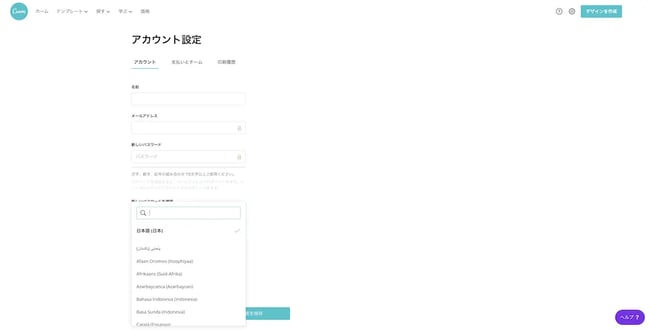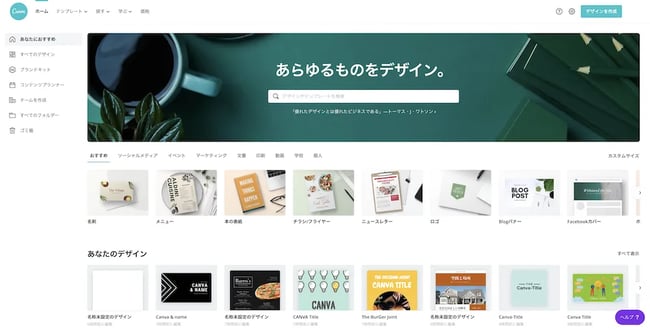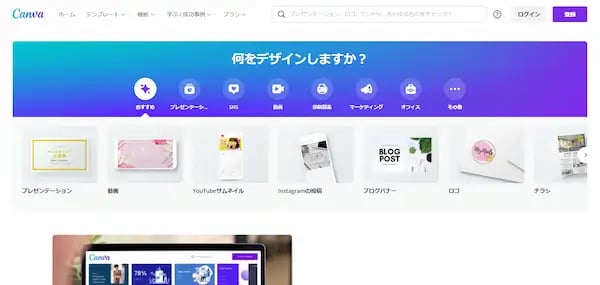
【Canva】無料で使える日本語フォントまとめ&選び方のコツを解説
手軽に高品質なデザインが作れると話題のCanvaは、実は日本語フォントが充実しています。ただ、使える日本語フォントが多すぎて、どれを選べば良いか迷う方も多いのではないでしょうか。
読みにくくなってしまったりデザイン全体と噛み合わなかったりと、ユーザー体験を損ねてしまう可能性があります。本記事では、Canvaの無料日本語フォントをまとめてご紹介した上で、フォント選びの基準や、日本語フォントを使えない場合の対処法も解説します。
Canvaとは
無料で使える豊富なテンプレートを活用することで、誰でも魅力的なデザインを作成できるデザインツールが「Canva」です。すべての人がデザインを自由に楽しめるよう支援することを目的に作られたツールで、1人ひとりがデザインの力で輝くことをミッションに開発されています。出典:PR TIMES
2021年時点で、無料で使えるテンプレートは25万点以上にも上り、ロゴやSNS投稿画像、YouTubeサムネイル、プレゼンテーション、チラシなど、さまざまなデザインが作成できます。PC版とスマホ版があり、PC版ではブラウザで利用できる点も特徴です。
Canvaには無料プランの他に有料プランとしてProとEnterpriseがあり、使用できるテンプレート数やチーム向け機能などに差があります。とはいえ、無料プランでも十分な機能性があり、個人や小規模チームを中心に広く利用されています。
Canvaの無料日本語フォント
Canvaでは日本ユーザーの声に応え、2021年8月に大量の日本語フォントを追加し、合計で309種類の日本語フォントを利用できるようになっています。一部は有料プランでのみ利用可能ですが、250を超えるほとんどの日本語フォントは無料プランで利用可能です。
では早速、Canvaで使える無料の日本語フォントの一部を紹介します。気になったものがあれば、デザイン作成時に試してみましょう。
ゴシック体
まずはゴシック体フォント9つです。
UD丸ゴ_ラージ
UD丸ゴ_ラージは、人気の丸ゴシック体の「スーラ」をベースに、モダン性を向上させたフォントです。スーラと比較して字面が大きくし、視認性と判別性が向上しています。
JKゴシック
JKゴシックJKゴシックは、その名の通り女子高生が書きそうな文字を意識した、全体丸みを帯びたフォントです。
さわらびゴシック
さわらびゴシックは、小さめの字であっても可読性が高いことが特徴的です。
せのびゴシックBold
せのびゴシックBoldせのびゴシックは、従来の「M+」フォントを全体的に縦に引き延ばしたような形で作られたフォントです。デザイン性を保ちながらも無機質な印象を与えます。
せのびゴシックRegular
やさしさゴシック
やさしさゴシックは、一般的なゴシック体と比べて、その名の通り「やさしさ」をコンセプトにおいたフォントです。漢字の対応も充実しています。
ロゴたいぷゴシック
ロゴたいぷゴシックは、その名の通りロゴや見出しに適したフォントで、角ばった印象と優しい印象が共存しています。
刻ゴシック
刻ゴシック刻ゴシックは、ゴシック体の形を保ちながらも、平仮名やカタカナは全体的に直線的な形を取り入れたフォントです。
ぼくたちのゴシック2
ぼくたちのゴシック2は、ぼくたちのゴシックからリニューアルしてできたもので、はねと丸みが印象的です。
明朝体
次は明朝体フォント7つです。
XANO明朝フォント
XANO明朝フォントは、手書き風に近いフォントで、各文字の書き出しなどに筆で書いたような墨溜まりが反映されています。
こころ明朝体
こころ明朝体こころ明朝体は、全体的に細めながらも、書き始めと書き終わりが丸くなっている点が印象的なフォントです。
はれのそら明朝
はれのそら明朝はれのそら明朝は、適度に一画が細く、こころ明朝体同様に墨溜まりが見られるような温かい印象を与えるフォントです。
はんなり明朝
はんなり明朝はんなり明朝は、平仮名とカタカナに特化したフォントです。それ以外の、漢字やアルフベットについては、IPA明朝体で表記される仕様になっています。
ほのか明朝
ほのか明朝ほのか明朝は、オーソドックスな明朝体をベースに、柔らかい曲線を取り入れたフォントです。
刻明朝
刻明朝刻明朝は、通常の明朝体がベースとなり、平仮名とカタカナのみを他よりも小さく設定して作られたフォントです。やや固めの印象を与えます。
梅明朝
梅明朝梅明朝は、梅フォントとも呼ばれ、源ノ角ゴシックと対の関係にあるようなフォントです。
行書体・筆文字系
行書体および筆文字系のフォントは5つあります。
おつとめフォント
ダーツフォント
みかちゃん
花鳥風月
衡山毛筆
手書き風
手書き風フォントは7つあります。
851チカラヅヨク
しねきゃぷしょん
はなぞめ
ふい字
たぬき油性マジック
桜鯰フォント
無心
その他
最後に、様々な独自フォントをご紹介します。全部で38個あります。
M+ 1m Bold
M+ 1m Regular
M+ 1m Thin
M+ Bold
M+ Heavy
M+ Rounded Black
M+ Thin
Rounded M+ 1p Black
Rounded M+ 1p Bold
Rounded M+ 1p Regular
Rounded M+ 1p Thin
Rounded M+ Black
Rounded M+ Bold
Rounded M+ Regular
Rounded M+ Thin
Noto Sans Black